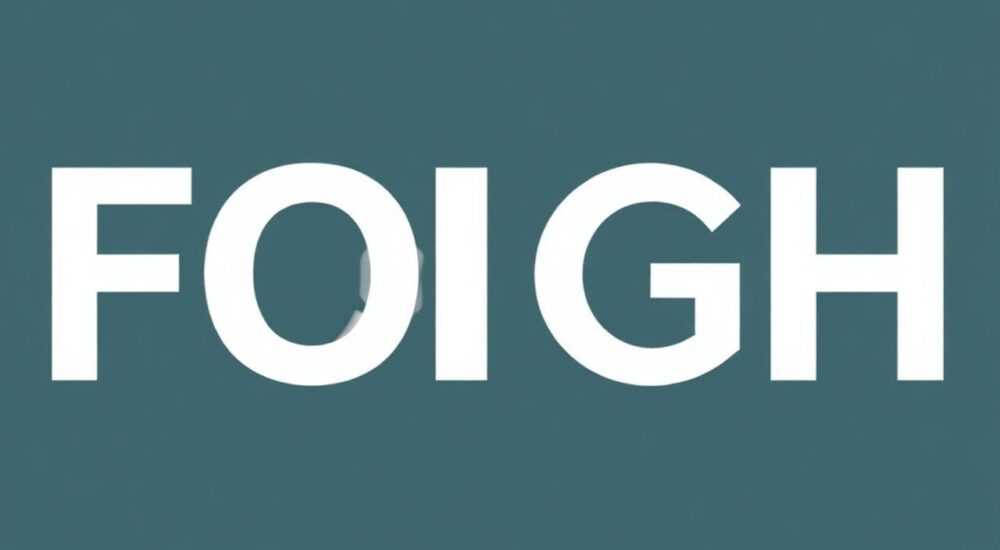
Как сделать шрифт толще в фигме
Чтобы сделать шрифт толще в Figma, нужно изменить его начертание (вес) через панель свойств — достаточно выбрать более жирное значение из выпадающего списка Weight или использовать числовые значения от 100 до 900. Если нужного веса нет в списке, это может быть связано с ограничениями выбранного шрифта: не все типографские семейства поддерживают широкий диапазон насыщенности. В таких случаях можно либо подобрать альтернативный шрифт с требуемыми начертаниями, либо применить имитацию жирности с помощью эффектов, хотя последний способ не рекомендуется для финальных макетов.
Figma — один из самых популярных инструментов для цифрового дизайна интерфейсов, графики и прототипирования. Благодаря своей облачной архитектуре, гибкости и глубокой настройке, платформа позволяет командам эффективно работать с текстовым контентом, включая точную типографскую настройку. Одним из ключевых параметров при работе с текстом является его толщина, или, как её часто называют, «вес шрифта». Правильная настройка веса влияет на читаемость, визуальную иерархию и общее восприятие дизайна. Однако у многих пользователей, особенно новичков, возникает вопрос: как именно увеличить толщину текста в Figma, если стандартные опции кажутся недостаточными?
Как изменить вес шрифта в Figma: пошагово
Чтобы изменить толщину текста в Figma, выполните несколько простых действий. Сначала выделите текстовый объект с помощью инструмента Text (T). В правой панели свойств найдите раздел Typography, где отображаются все параметры шрифта: семейство, размер, интерлиньяж, кернинг и другие. В строке Weight вы увидите текущее значение — например, Regular (400) или Medium (500).
Для изменения толщины кликните по полю Weight. Откроется выпадающий список с доступными начертаниями. Обычно они обозначаются как Thin, Light, Regular, Medium, SemiBold, Bold, ExtraBold и Black, соответствующие числам от 100 до 900. Выберите более высокое значение, чтобы сделать шрифт толще. Например, переключение с Regular (400) на Bold (700) значительно усиливает визуальное воздействие текста.
Если вы предпочитаете точность, Figma позволяет вводить числовые значения вручную. Просто введите нужное число (например, 600), и система применит ближайшее доступное начертание. Это удобно при работе с дизайн-системами, где требуется строгое соответствие типографским гайдлайнам.
- Выделите текстовый слой с помощью инструмента Text (T).
- Перейдите в правую панель свойств и найдите параметр «Weight».
- Кликните по текущему значению и выберите более жирное начертание из списка.
- При необходимости введите числовое значение вручную для точной настройки.
Быстрая проверка доступных начертаний
Перед тем как менять вес, убедитесь, что шрифт действительно поддерживает нужные варианты. Некоторые бесплатные или урезанные версии шрифтов содержат только одно или два начертания. Чтобы проверить, какие веса доступны, нажмите на стрелку рядом с названием шрифта — Figma покажет список всех установленных вариаций. Если там нет Bold или SemiBold, значит, их нужно добавить.
Поддержка шрифтов: почему не все веса доступны
Один из самых частых источников путаницы — отсутствие нужных весов в списке выбора. Пользователь ожидает увидеть Bold, но видит только Regular. Причина проста: не каждый шрифт имеет полный набор начертаний. Шрифтовое семейство может включать только одну или две версии, особенно если это бесплатный или упрощённый вариант.
Например, Google Fonts предлагает тысячи шрифтов, но не все из них имеют расширенную шкалу весов. Roboto поддерживает от 100 до 900, в то время как более редкие шрифты могут иметь только 400 и 700. Аналогично, локальные шрифты, установленные на компьютере, могут быть загружены в Figma не полностью, если пользователь не синхронизировал все файлы.
Чтобы решить проблему, зайдите в Figma Desktop или через браузер в раздел шрифтов (File → Settings → Fonts) и убедитесь, что все нужные начертания синхронизированы. Для Google Fonts достаточно включить синхронизацию в настройках. Для локальных шрифтов — установите недостающие .ttf или .otf файлы на компьютер и перезапустите Figma.
Как добавить недостающие начертания